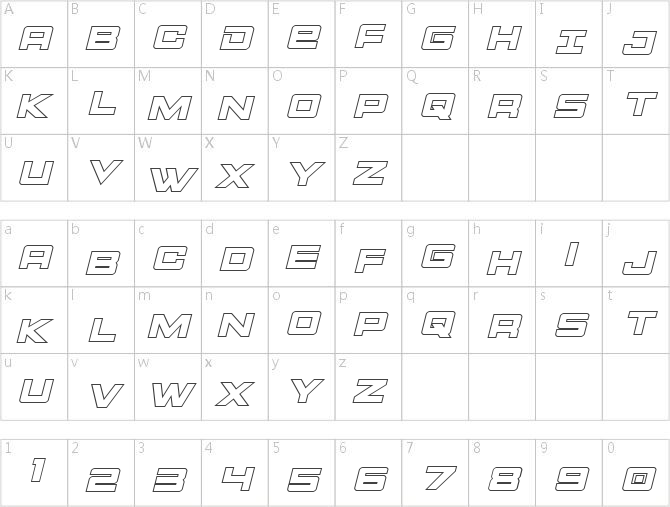
Montroc Outline Italic 詳情頁(yè)
Montroc Outline Italic字體字庫(kù)是一款讓人賞心悅目、百看不厭的英文字體,適合各類廣告和產(chǎn)品包裝設(shè)計(jì)應(yīng)用,字體大小0.04MB,格式為ttf字體,上傳用戶是韓國(guó)露韓,作者/版權(quán)方為未知